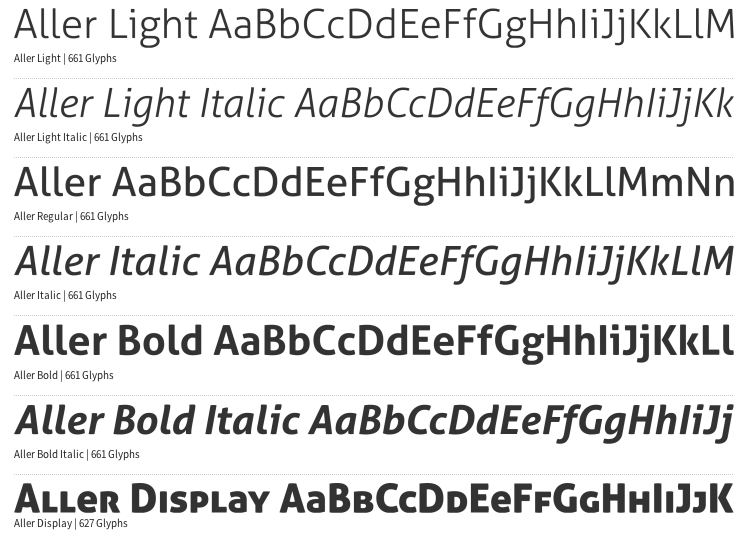
Aller STD 1.0
Die Aller-Schriftfamilie wurde 2008 für die Danmarks Medie- og Journalisthøsjkole gestaltet und vom Verleger Aller großzügig gesponsort. Die Schrift ist für bis zu 25 Nutzer innerhalb einer Organisation kostenlos nutzbar.
Marc Weymann